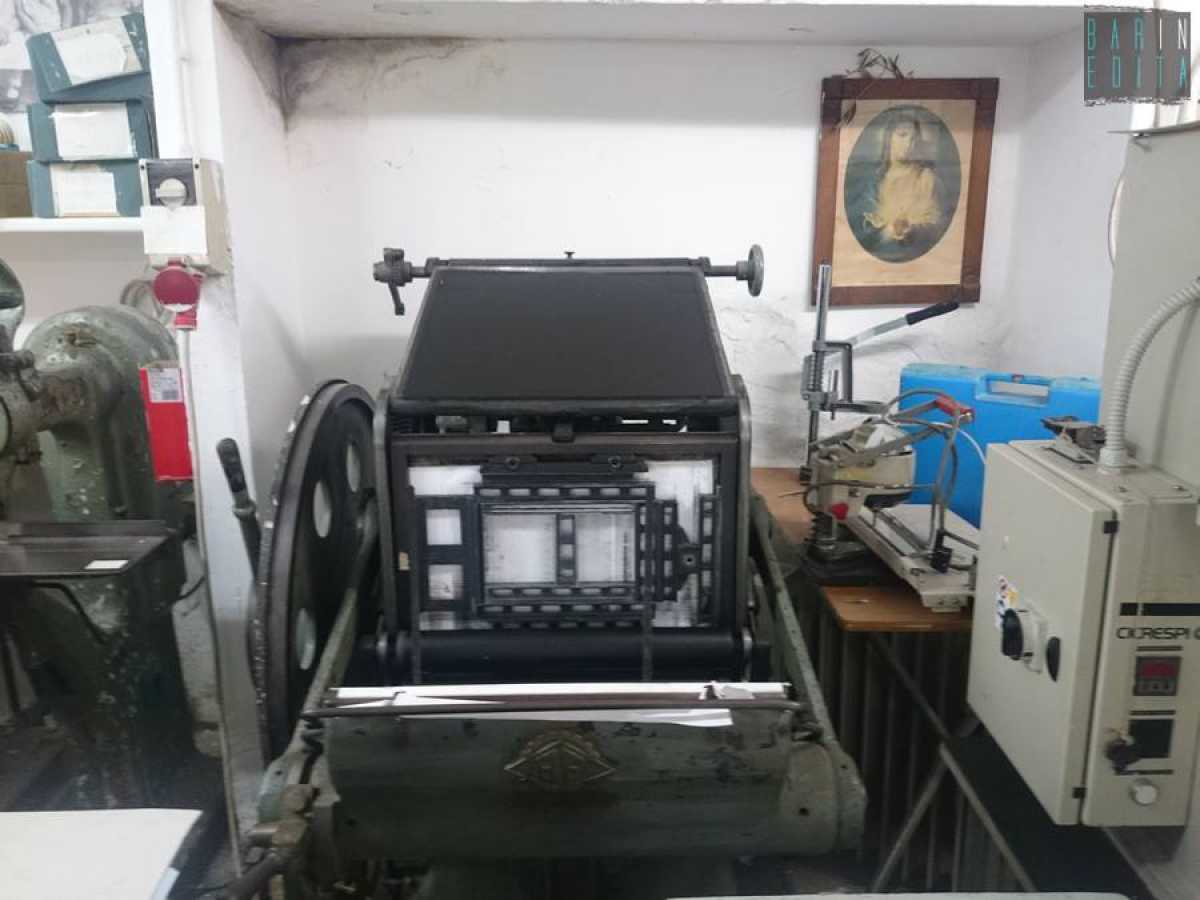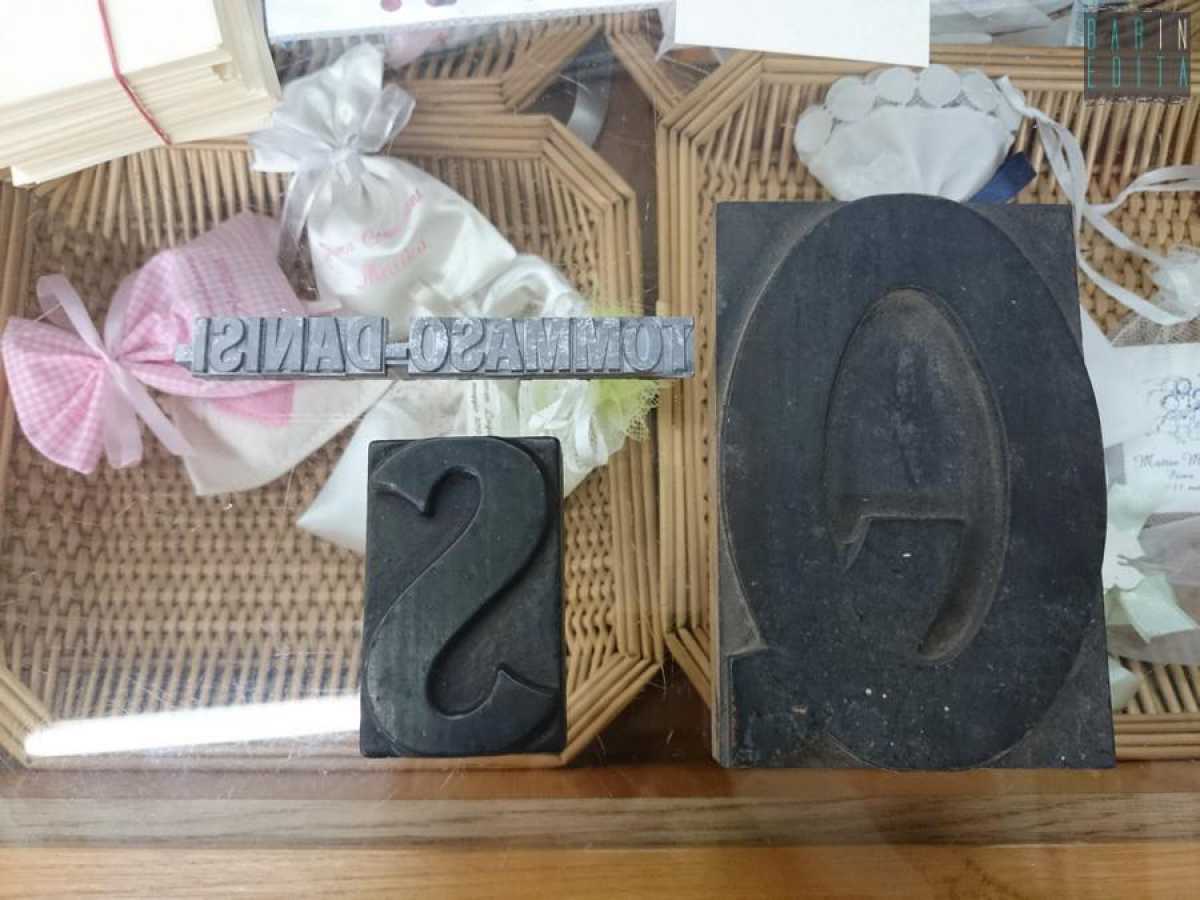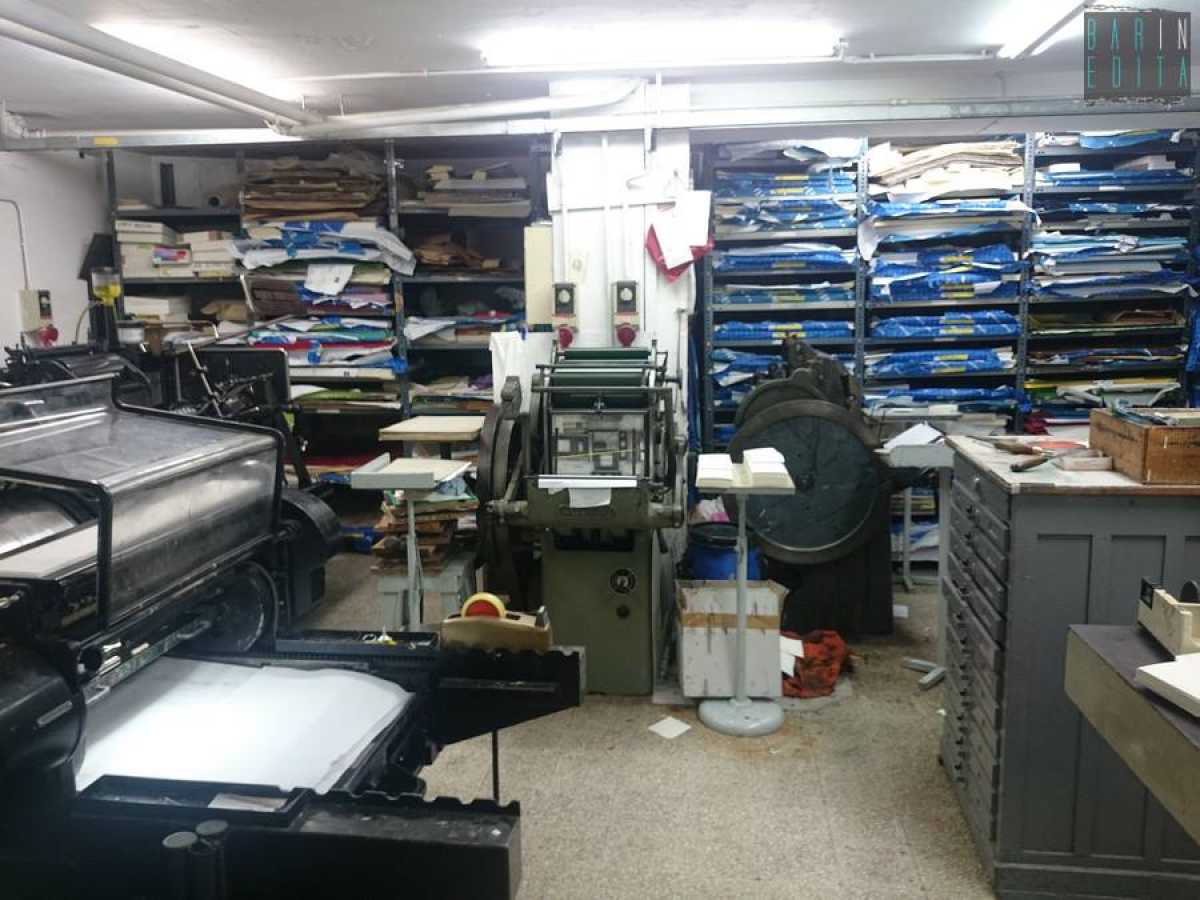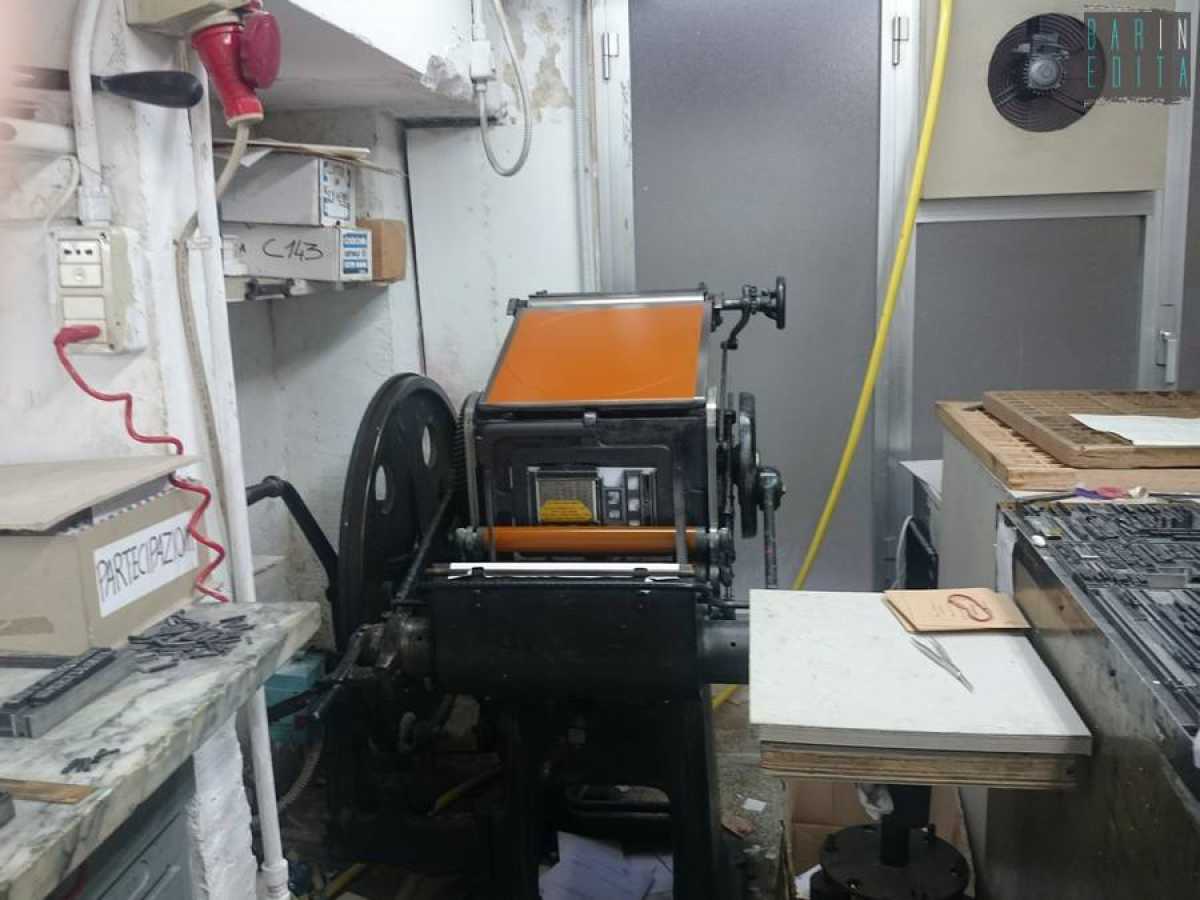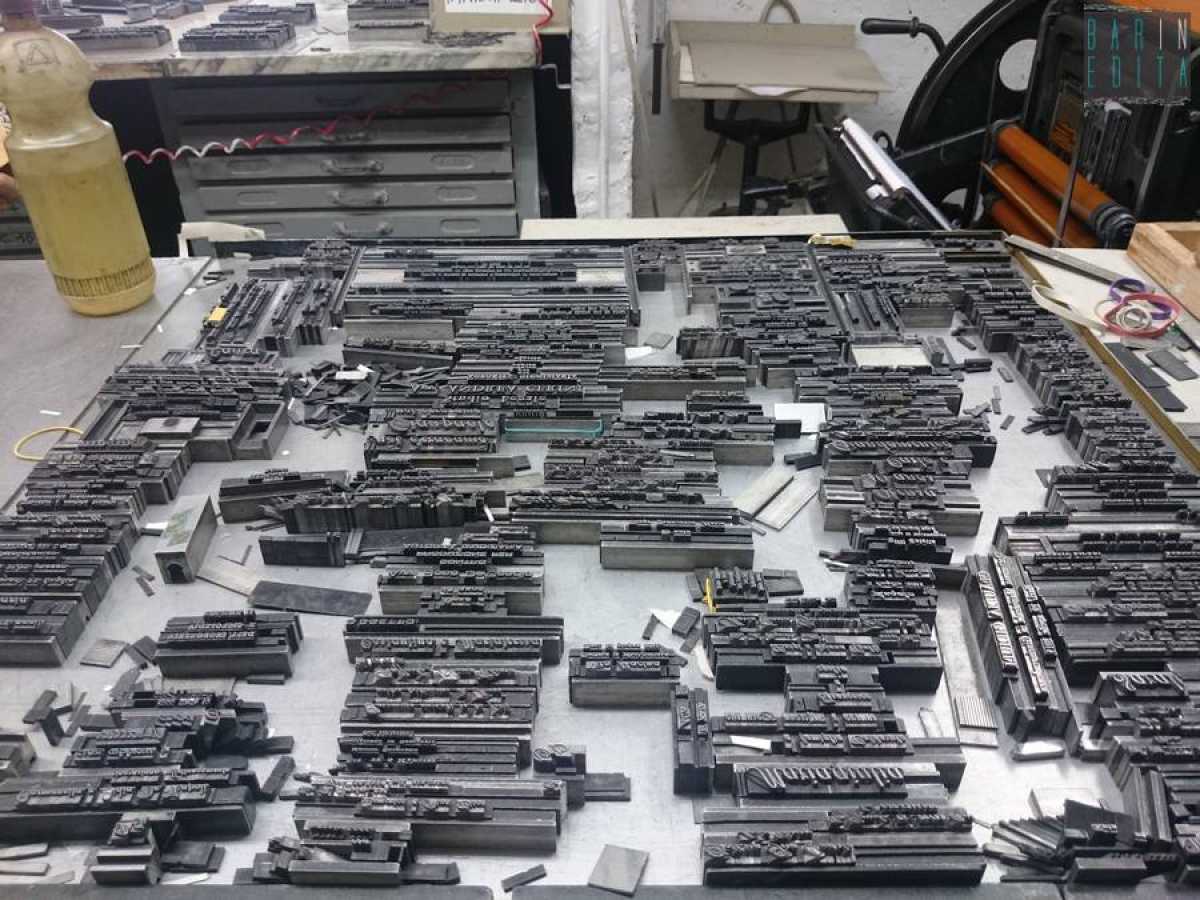
Bari, la tipografia con i caratteri mobili
A Bari nella storica tipografia Danisi di via Davanzati (attiva dal 1934), si stampa ancora con i caratteri mobili ideati da Gutenberg
La tipografia Danisi di via Davanzati. Sulla sinistra, al bancone, la proprietaria 72enne Giovanna Danisi
Il laboratorio tipografico, collocato al piano inferiore, dove si stampa ancora con i caratteri mobili
Una macchina da stampa risalente al 1800 e ancora funzionante
Un secondo antico macchinario: è possibile notare l'inchiostro che attraverso i rulli passerà sui caratteri